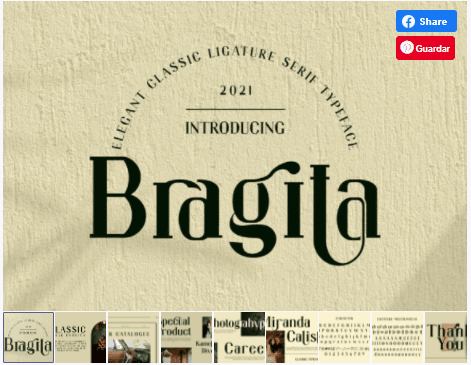
Bragita Fuente Font
Bragita - элегантный и современный шрифт с засечками. Он одновременно современный и ностальгический, и отлично подходит для логотипов, журналов и сообщений в социальных сетях. Для тех из вас, кто нуждается в стильном, стильном и шикарном дизайне, этот шрифт был создан специально для вас!